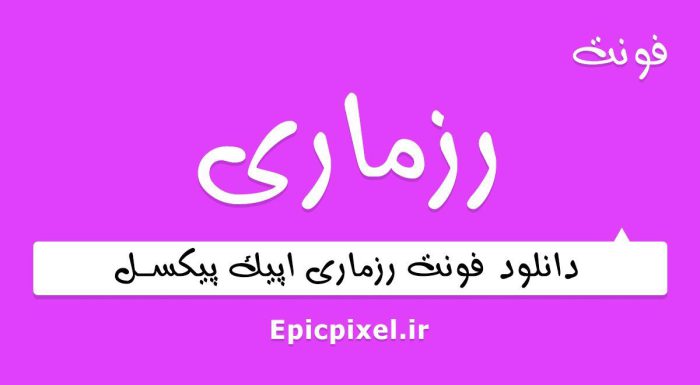
فونت رزماری فارسی
فونت رزماری فارسی ترکیبی از زیبایی دست نویس و کارایی حرفه ای است که آن را به گزینه ای بی نظیر برای طراحان تبدیل کرده. این فونت رایگان با الهام از سبک مدرن ، تمامی حروف فارسی را پشتیبانی می کند و برای لوگو ، بنر و پروژه های گرافیکی ایده آل است.
طراحی طبیعی و انعطاف پذیر آن، حس نوشتار دستی اصیل را به تصویر می کشد و با خوانایی بالا در هر اندازه ای ، برای متن های طولانی و تیترها مناسب است.